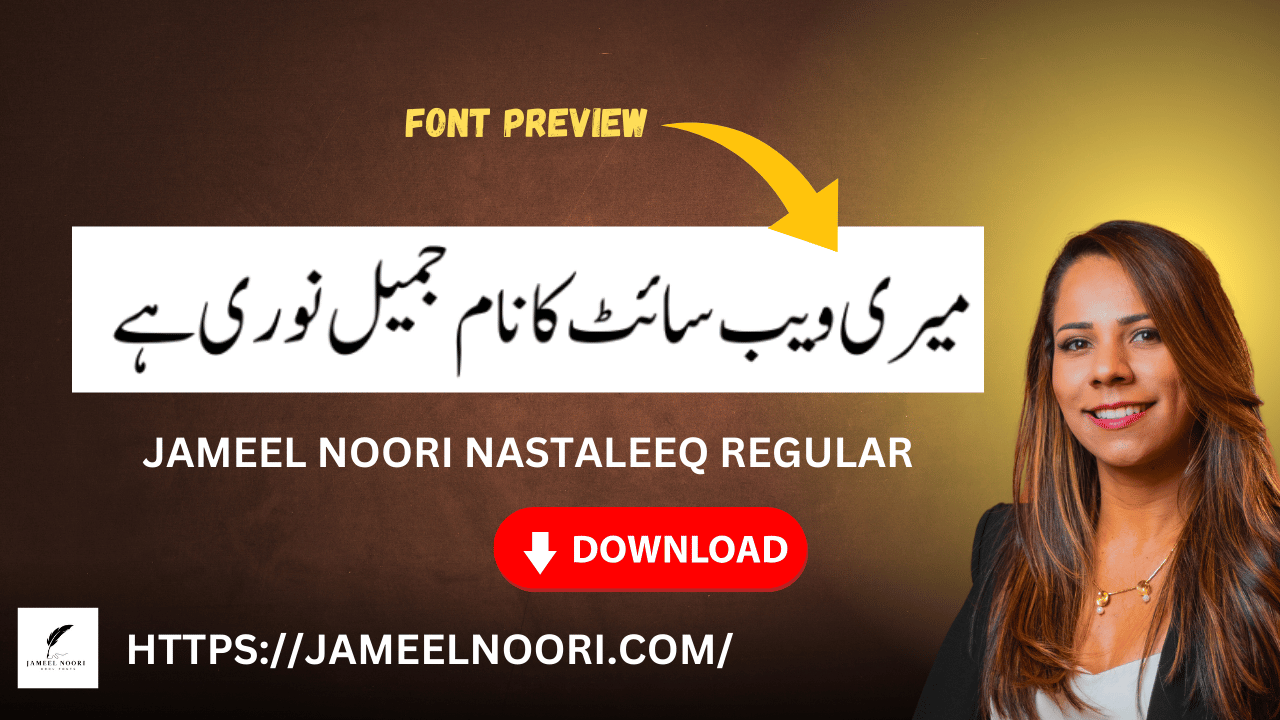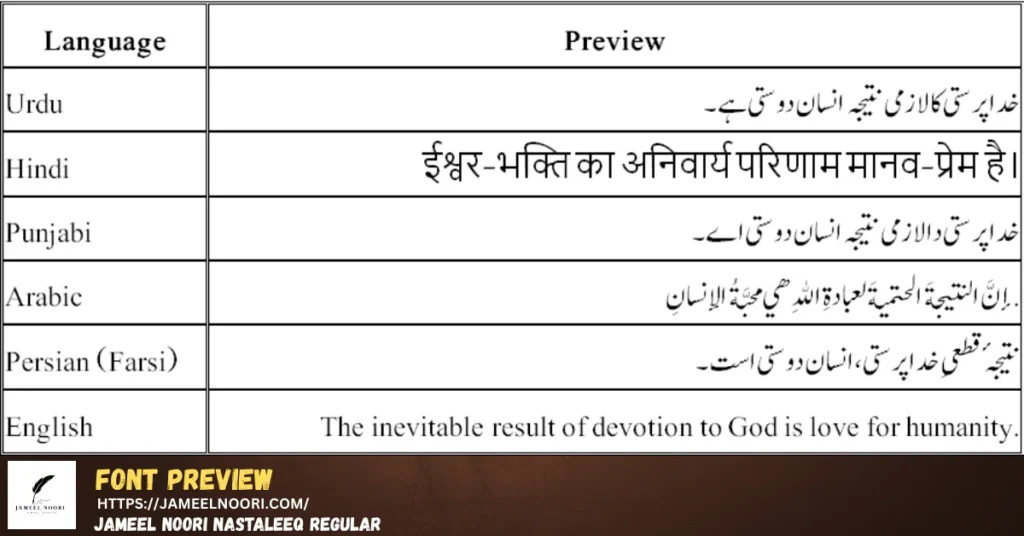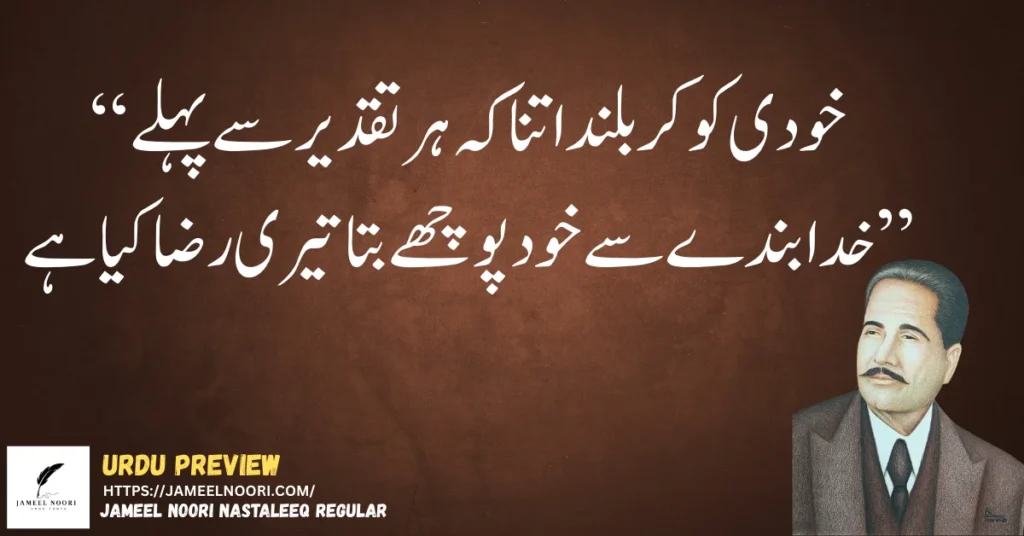
Jameel Noori Nastaleeq Regular Download Urdu Font
What Is Jameel Noori Nastaleeq Urdu Font?
Jameel Noori Nastaleeq Urdu Font aik Unicode-based font hai jo traditional Nastaleeq writing style par design kiya gaya hai. Iska look handwritten Urdu ke bohat qareeb hota hai, jis ki wajah se ye long reading content ke liye bohat suitable mana jata hai.
Purane Urdu fonts zyada tar InPage tak limited thay, lekin Jameel Noori modern systems, browsers, aur mobile devices par bhi perfect kaam karta hai — isi liye ye itna popular hai.
History of Jameel Noori Regular Urdu Font
Digital Urdu typography ki bunyaad 1981 mein rakhi gayi jab Ahmed Mirza Jamil ne Noori Nastaleeq develop kiya. Ye aik historic achievement thi kyun ke pehli dafa complex Nastaleeq script computers par possible hui.
Baad mein Jameel Noori Nastaleeq aik modern Unicode font ke taur par introduce hua jo Noori Nastaleeq se inspired tha. Available records aur font repositories ke mutabiq, ye font early 2000s mein public use ke liye aaya, jab ke zyada common versions 2008 ke around circulate hue. Iska main goal ye tha ke Nastaleeq Urdu ko InPage se bahar laa kar modern platforms par usable banaya jaye.
Jameel Noori Nastaleeq vs Kasheeda Version
Aksar users ko aik hi font ke mukhtalif versions dekh kar confusion hoti hai.
• Jameel Noori (Standard Version):
Daily Urdu typing, blogging, aur website content ke liye use hota hai.
• Jameel Noori Nastaleeq Kasheeda:
Ye aik layout-optimized version hai jo text justification aur spacing ko improve karta hai, khas tor par books, newspapers, aur long paragraphs ke liye.
Kasheeda version ki koi alag history nahi hoti, ye sirf visual balance behtar banata hai.
Who Is the Owner or Designer of Jameel Noori Font?
Is font ka koi clearly documented official owner ya company Google ya major font databases par mention nahi milti. Kai font files mein author ka naam generic hota hai ya bilkul missing hota hai.
Haan, digital Nastaleeq typography ka asli credit Ahmed Mirza Jamil ko jata hai, jinki Noori Nastaleeq ne baad ke kai fonts ko inspire kiya, jin mein Jameel Noori bhi shamil hai. Aaj ke daur mein Jameel Noori ko aik community-distributed Urdu font kaha jata hai.